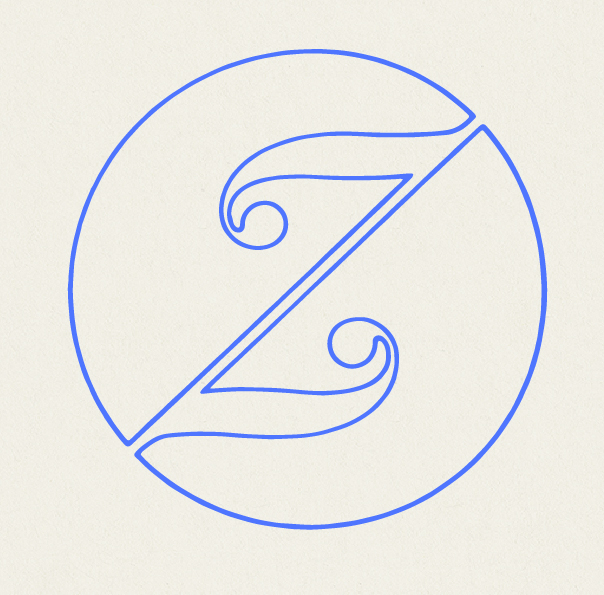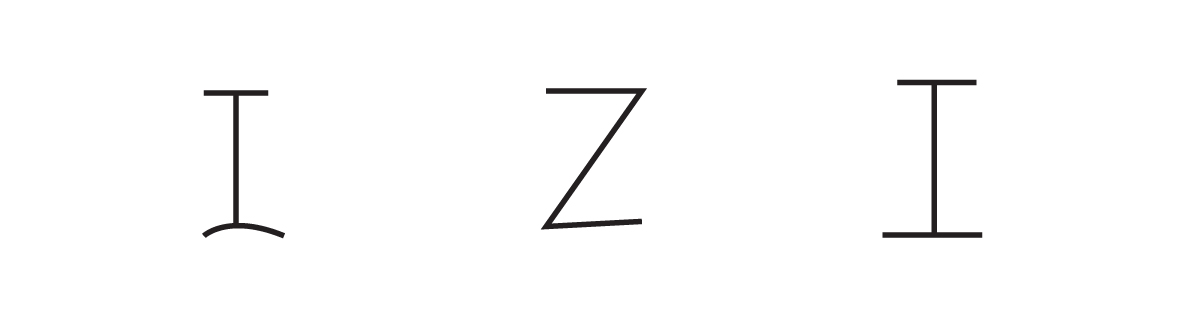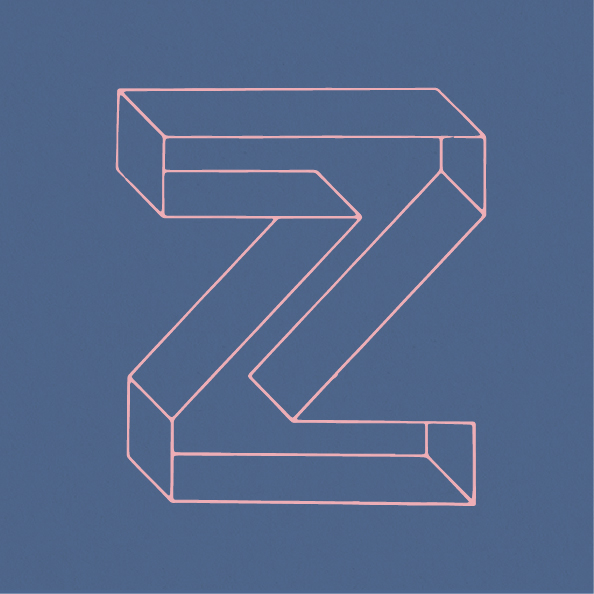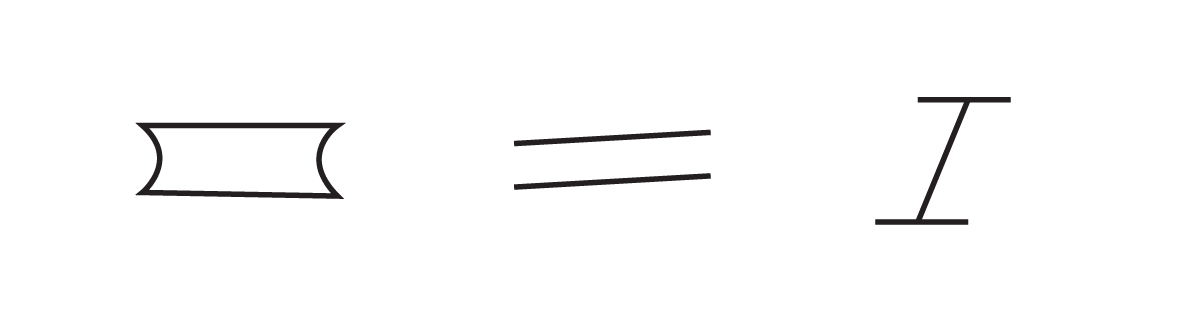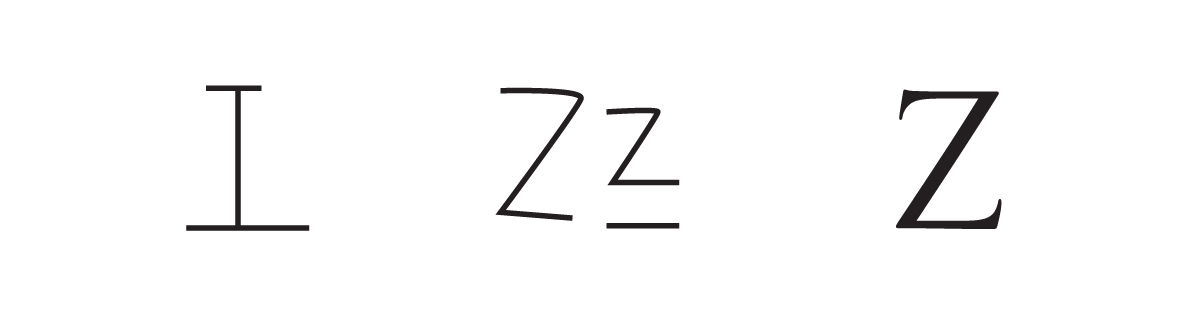
Jeroglífico 3000 aC • Sinalítico 1600 aC • Fenicio 1100 aC
Griego arcaico 800 aC • Griego oriental 400 aC • Griego occidental 400 aC
Etrusco 800 aC • Latín clásico 200 aC • Romano 100 aC
Vigésima novena letra del abecedario español, y vigésima sexta del orden latino internacional. Su nombre es zeta (es la única letra que conservó su nombre griego como tal).
La letra “Z” viene de la semita zayin y de la griega zeta.
Se estima que su forma proviene del zai fenicio, cuyo significado en arameo es arma.
Fue adoptada por los etruscos para su alfabeto, pero no así para los romanos, que no la incorporaron hasta después de la conquista de Grecia, como en el caso de la “Y”. Es entonces que fue colocada al final del alfabeto.
Su minúscula ha conocido numerosas variantes caligráficas.
| Del alfabeto Labyrinthe, diseñado por Jean Larcher en 1976 |
Zinc Development Association, diseño Crosby, Fletcher & Forbes, Inglaterra.1979 |
Novarese book itálica
Impact |
| Diseño de Michele Provinciali para Zanotta, Italia. c1960 |
PEZ, marca austríaca de caramelos (1927). |